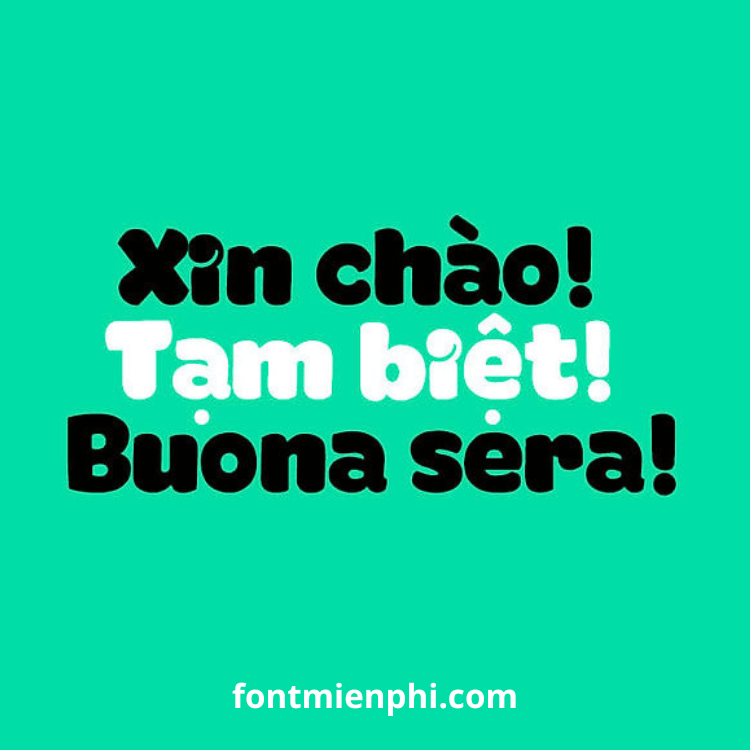
Việt hóa font iCiel Koni
Font chữ đóng vai trò quan trọng trong thiết kế, giúp sản phẩm trở nên chuyên nghiệp và ấn tượng hơn. Nếu bạn đang tìm kiếm một font chữ độc đáo, phong cách, iCiel Koni là một lựa chọn tuyệt vời. Bài viết này sẽ giới thiệu chi tiết về font iCiel Koni Việt hóa, lợi ích khi sử dụng và cách tải miễn phí tại Fontmienphi.com.
1. Giới Thiệu Font iCiel Koni Việt Hóa
Font iCiel Koni là một trong những font chữ sans-serif hiện đại, được thiết kế với nét chữ mềm mại nhưng không kém phần cá tính. Phiên bản Việt hóa đã được tối ưu để hỗ trợ đầy đủ Tiếng Việt, giúp bạn thoải mái sáng tạo trong các dự án thiết kế, in ấn, logo, banner mà không lo lỗi font.
✔ Hỗ trợ Tiếng Việt đầy đủ – Không bị lỗi font khi gõ dấu.
✔ Phong cách hiện đại, trẻ trung – Phù hợp với thiết kế logo, poster, quảng cáo.
✔ Đa dạng kiểu chữ – Nhiều độ đậm nhạt (Light, Regular, Bold).